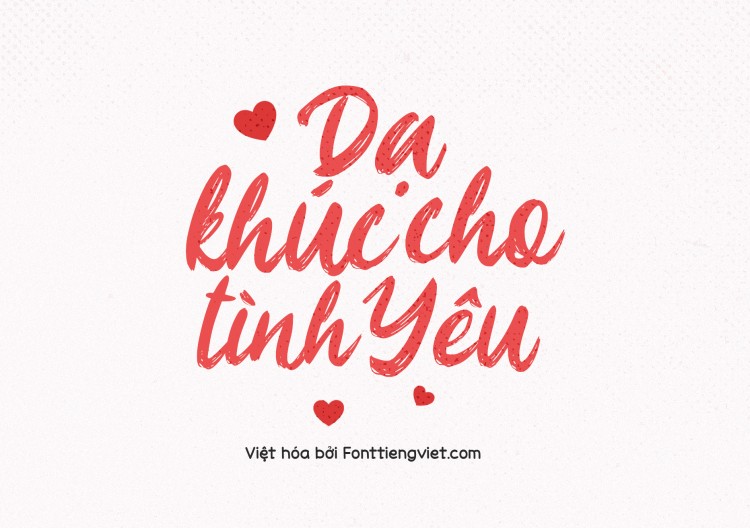
Font việt hóa 1FTV Playbrush
Trong thế giới thiết kế đồ họa hiện đại, việc tìm kiếm một Font Miễn Phí mang đậm cá tính riêng là điều vô cùng quan trọng. Font việt hóa 1FTV Playbrush nổi lên như một lựa chọn hàng đầu cho những ai yêu thích phong cách nghệ thuật phóng khoáng. Đây là bộ font chữ dạng cọ vẽ (brush) được tinh chỉnh kỹ lưỡng, hỗ trợ đầy đủ bộ gõ tiếng Việt, giúp các bạn học sinh và nhà thiết kế dễ dàng truyền tải thông điệp sáng tạo vào sản phẩm của mình mà không lo lỗi font.
Đặc điểm nổi bật của Font việt hóa 1FTV Playbrush
Bộ font này mô phỏng những nét vẽ tay mạnh mẽ, đầy ngẫu hứng nhưng vẫn đảm bảo được sự tinh tế trong từng đường nét. 1FTV Playbrush đặc biệt phù hợp cho các thiết kế tiêu đề, bìa sách, poster sự kiện hoặc các dự án truyền thông học đường cần sự năng động.
Tính ứng dụng cao trong thiết kế
Với cấu trúc nét đậm nhạt rõ rệt, Font việt hóa 1FTV Playbrush tạo ra hiệu ứng thị giác mạnh mẽ, giúp nội dung trở nên nổi bật hơn bao giờ hết. Người dùng có thể kết hợp font này với các tông màu rực rỡ để tạo nên những tác phẩm mang đậm dấu ấn cá nhân hoặc phong cách nghệ thuật đường phố độc đáo.
Cách sử dụng Font việt hóa 1FTV Playbrush hiệu quả
Để phát huy tối đa vẻ đẹp của bộ font, bạn nên sử dụng chúng cho các cụm từ ngắn hoặc tiêu đề chính. Việc lạm dụng quá nhiều chữ trong một đoạn văn bản dài có thể gây rối mắt do đặc thù nét brush dày. Hãy thử thay đổi kích thước và khoảng cách giữa các chữ cái để tạo ra sự cân bằng hoàn hảo cho bố cục tổng thể.